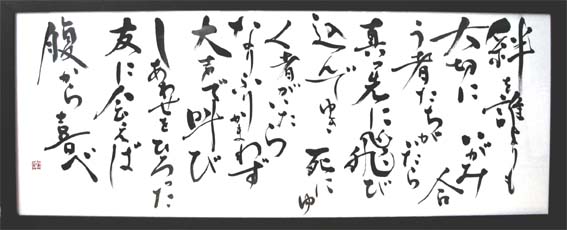
【書 「勇気の花」】 紙の大きさ:縦35cm×横90cm 仕上げ:マットなし額装 (兵庫県:大浜様) |
| 娘さんが生まれた記念に、「人生を常に前向きに生き且つ、いつでも自分に人に心に花を咲かせられる様な、力が漲りそして優しい感じで」とのご依頼でした。作品になっているこの詩は、大浜さまの好きな長渕剛さんの「勇気の花」の一部。人はひとりでは生きてゆけないから、人との繋がりを大切にしてほしい──。そんな大浜さまの思いが、この書を通して娘さんに伝わるよう、私も気持ちをこめて書かせて頂きました。さあ仕上げの額装、というところでハプニング発生!